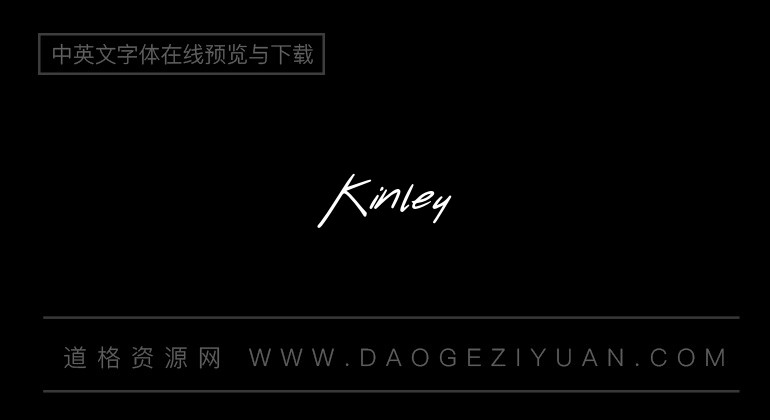
Kinley 是一种流行的西文字体。它的设计师是Jeremy Dooley,最初由Insigne Design公司发布。该字体最初于2011年推出,是一款优雅、现代化的字体,具有非常清晰和可读的特点。 Kinley 字体包括多种字重,从轻到黑,适用于各种设计项目。它的特点是斜度较大的倾斜字母,这使得它在设计中常常被用于突出强调标题和短语的效果。 Kinley 字体的字母有着圆润的形状和清晰的线条,展现出一种现代感和时尚感。 总的来说,Kinley 字体是一种高质量、多功能的字体,适用于各种设计项目,包括品牌标识、海报、广告和网站设计等。内容介绍
Kinley是一款非常不错的手写艺术字体,具有很好的视觉感,适合于文化类的宣传设计、商业类品牌的广告和产品包装设计以及个性化文字排版等较多场景。